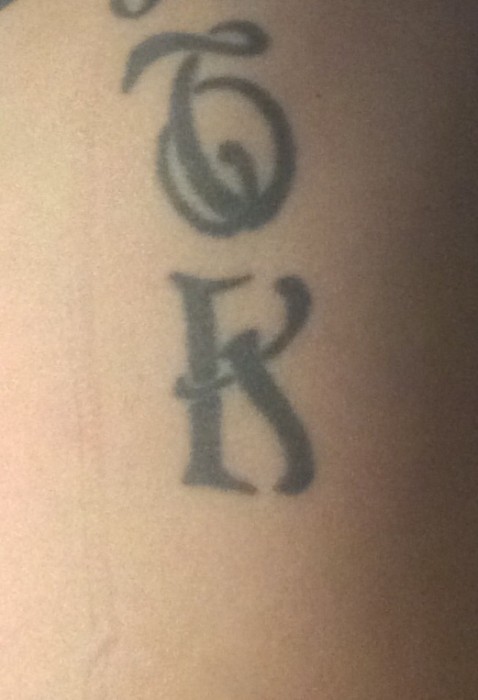
Benötige Hilfe! Welche Schriftart ist das? (Tattoo-Versalien)
Da würde ich den Tattoo-Künstler fragen, ob der seiner Schrift einen Namen gegeben hat.
Ich glaube jedoch, dass der seinen Tattoo-Entwurf gezeichnet hat, ohne der Schrift jetzt auch noch einen Namen zu geben.
Man kann nämlich Schrift einfach so zeichen, ohne dass man sich jetzt an eine vorhandene Schrift genau hält. Ich weiß das, hab ichs doch schon oft gemacht.
Nein, das ist ganz sicher nicht vom Tätowierer selbst gezeichnet. Hätte nämlich selbst diese Schrift vor mind. 8 Jahren mal gefunden gehabt. Leider weiß ich nicht mehr wo und wie sie heißt
Das glaube ich auch nicht, dass der Tätowierer das selbst gezeichnet hat  :neenee:
Vielleicht hat er das aus Vorlagenheftchen oder -Büchern oder es ist irgendein Freefont ...
Ich kann mir nicht helfen, das K sieht aus, als stünde es vor der verschlossenen Toilettentür und muß mal ganz dringend …
Wenn das eine Schrift ist, dann von den einschlägigen Seiten kruder Freefonts.